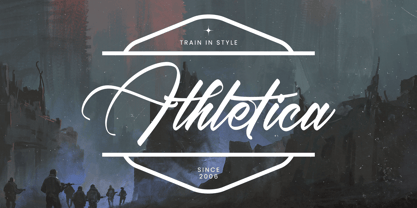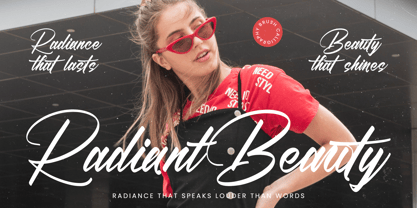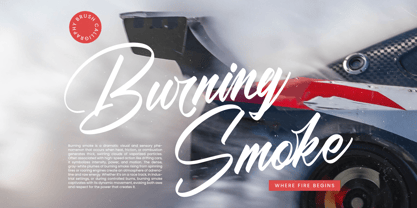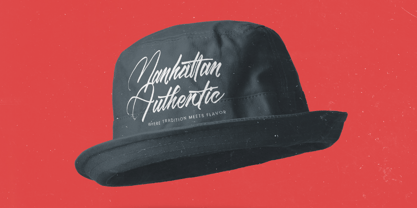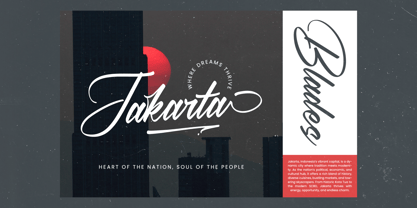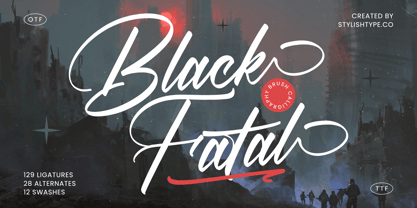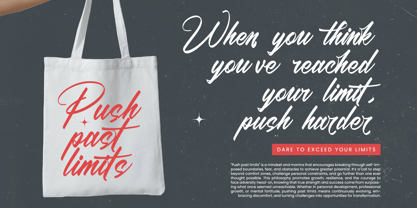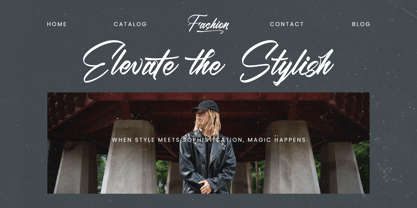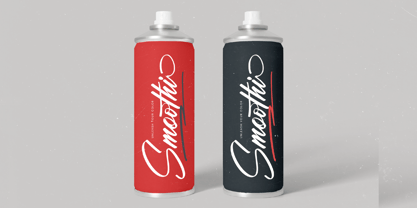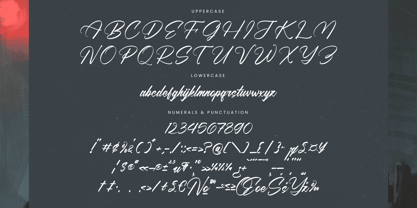
Black Fatal
La familia tipográfica Black Fatal fue diseñada por Heru Utama Putra y publicada por Stylishtype Studio. Black Fatal contiene 2 estilos y opciones de paquete familiar. Más información sobre esta familia
Black Fatal - Brush Calligraphy Font , from Stylishtype, Suitable for any projects such as: logos, branding projects, homeware designs, product packaging, mugs, quotes, posters, shopping bags, t-shirts, book covers, name card, invitation cards, greeting cards, label, photography, watermark, special events, and all your other luxury and beautiful projects that need a Luxury Script taste.